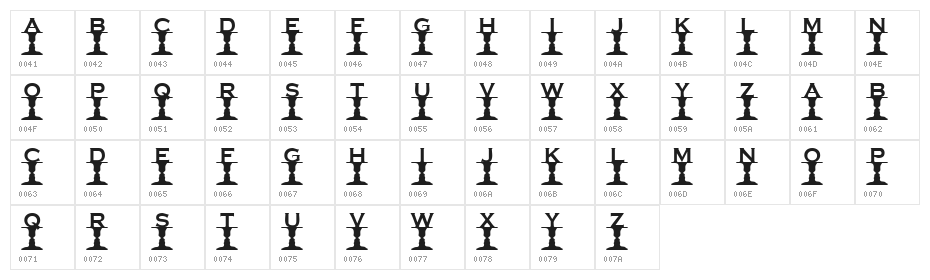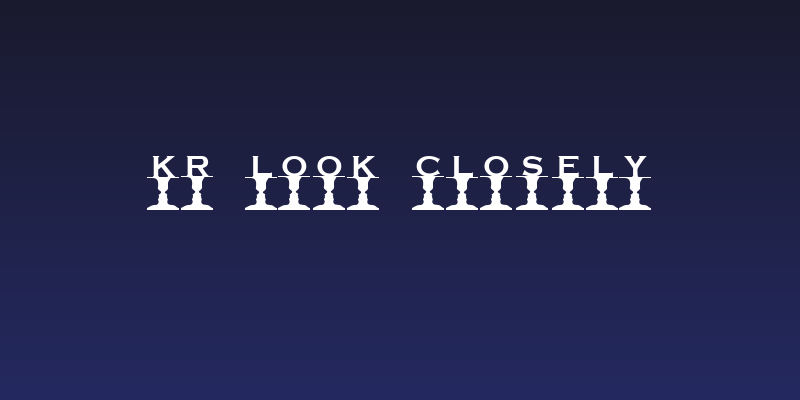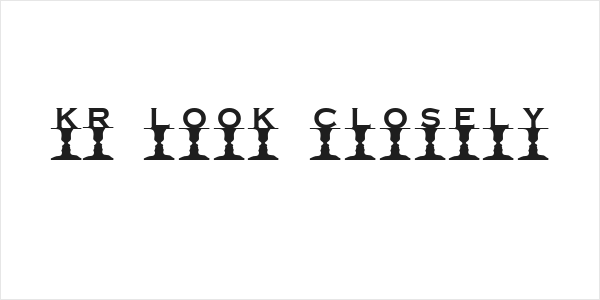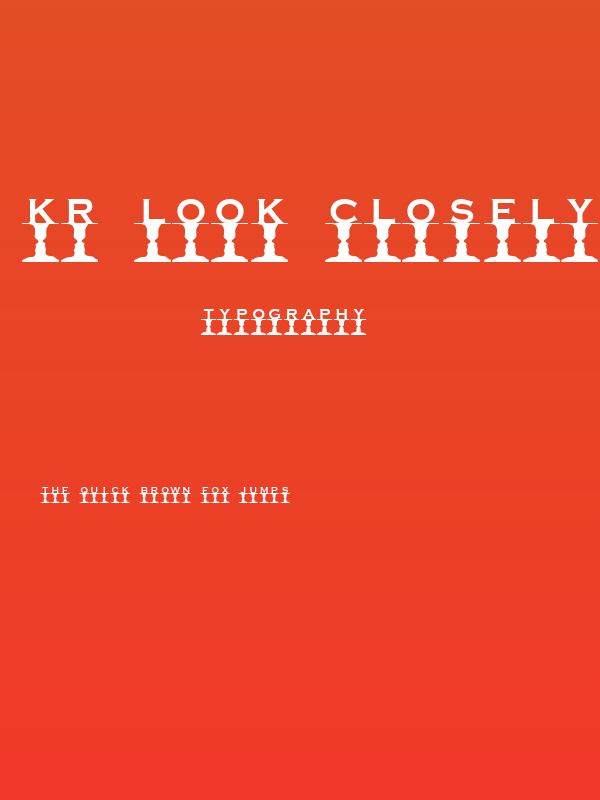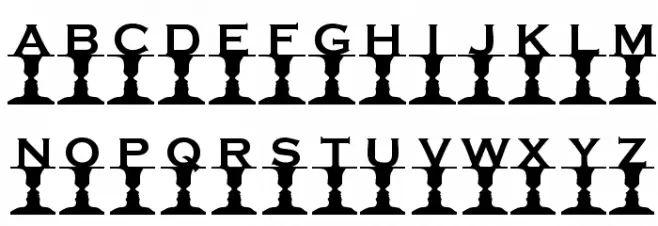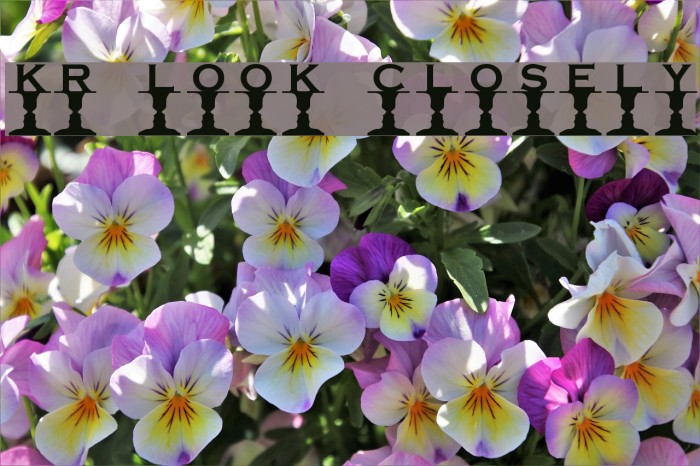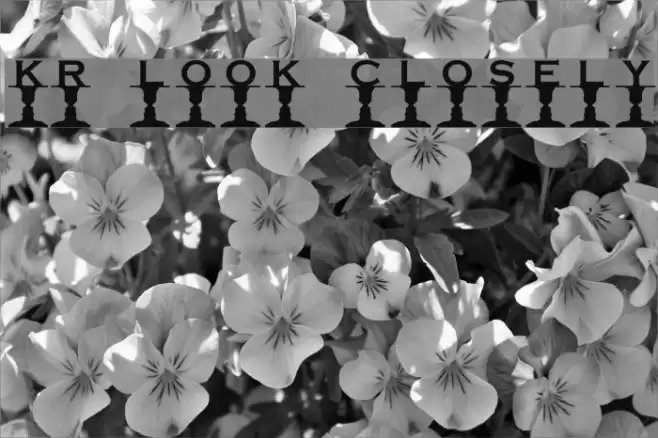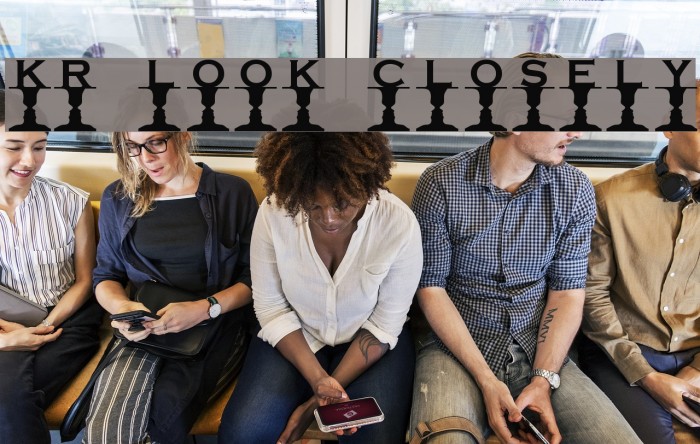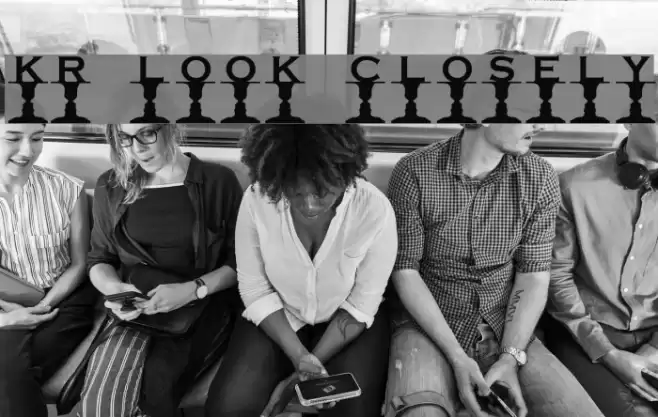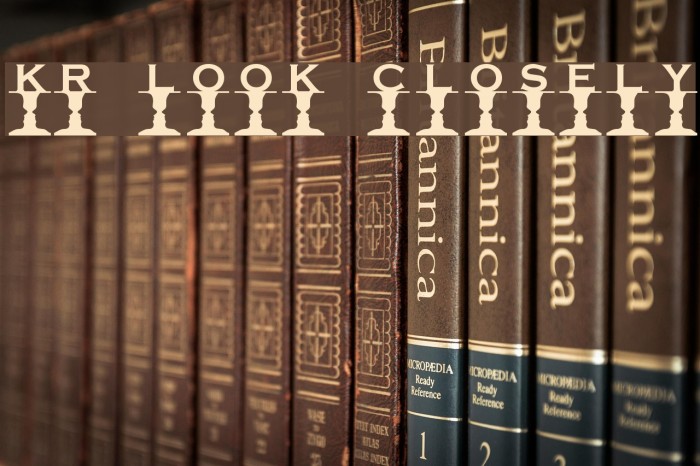
KR Look Closely Font
| 用途 | Logos, Headlines, Themed Events |
| おすすめプロジェクト | Ideal for chess-related branding, game design, educational materials, or themed event promotions. |